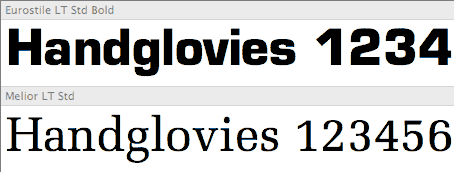
Eurostile ist als Logofont gesetzt. Was passt dazu?
Ich würde auch die Headlines in Eurostile machen und suche eine (Semi-?)Serif die dazu passt … Ist für den Bereich Bausoftware, Anwendung auf einem Poster. Wenig Text.
Was meint ihr dazu?
Ich würde zur Eurostile die Melior testen. Das gespann kommt dann zwar ziemlich Retro daher, aber mit dem gemeinsamen klassizistischen Zug und der Super-Ellipse könnten die beiden schon ein recht gutes Gespann bilden. (Ausserdem ist die Melior sehr robust und auch in kleinen Schriftgraden sehr gut lesbar.)
Dann mach's doch einfach ganz "unähnlich" ...
Kann funktionieren, muss aber nicht.